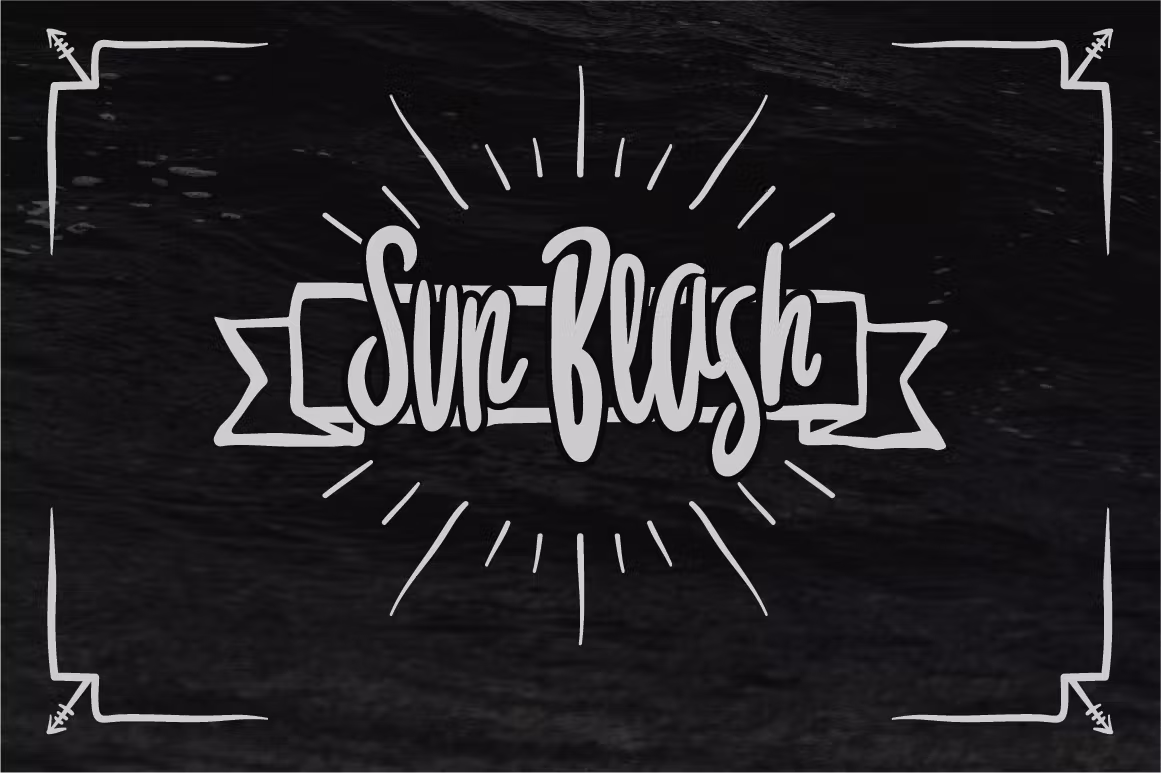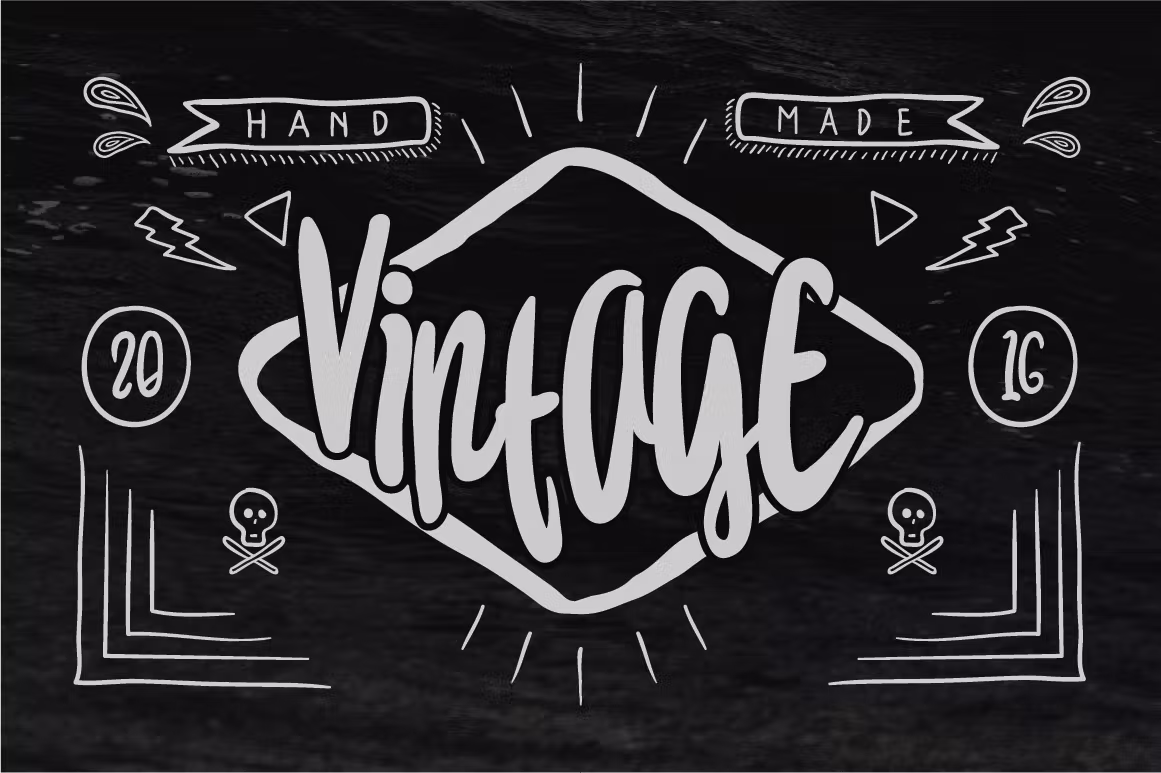
Blowing Typeface Font
Description de Blowing Typeface Font
Présentation de BLOWING Typeface, la police faite à la main peut rendre votre design plus époustouflant et plus impressionnant. BLOWING Typeface est parfait pour créer du design : affiches, une variété de citations, en-têtes, créations de logos, en-têtes de blog, toutes sortes de couvertures, T-shirts, tasses, etc. .